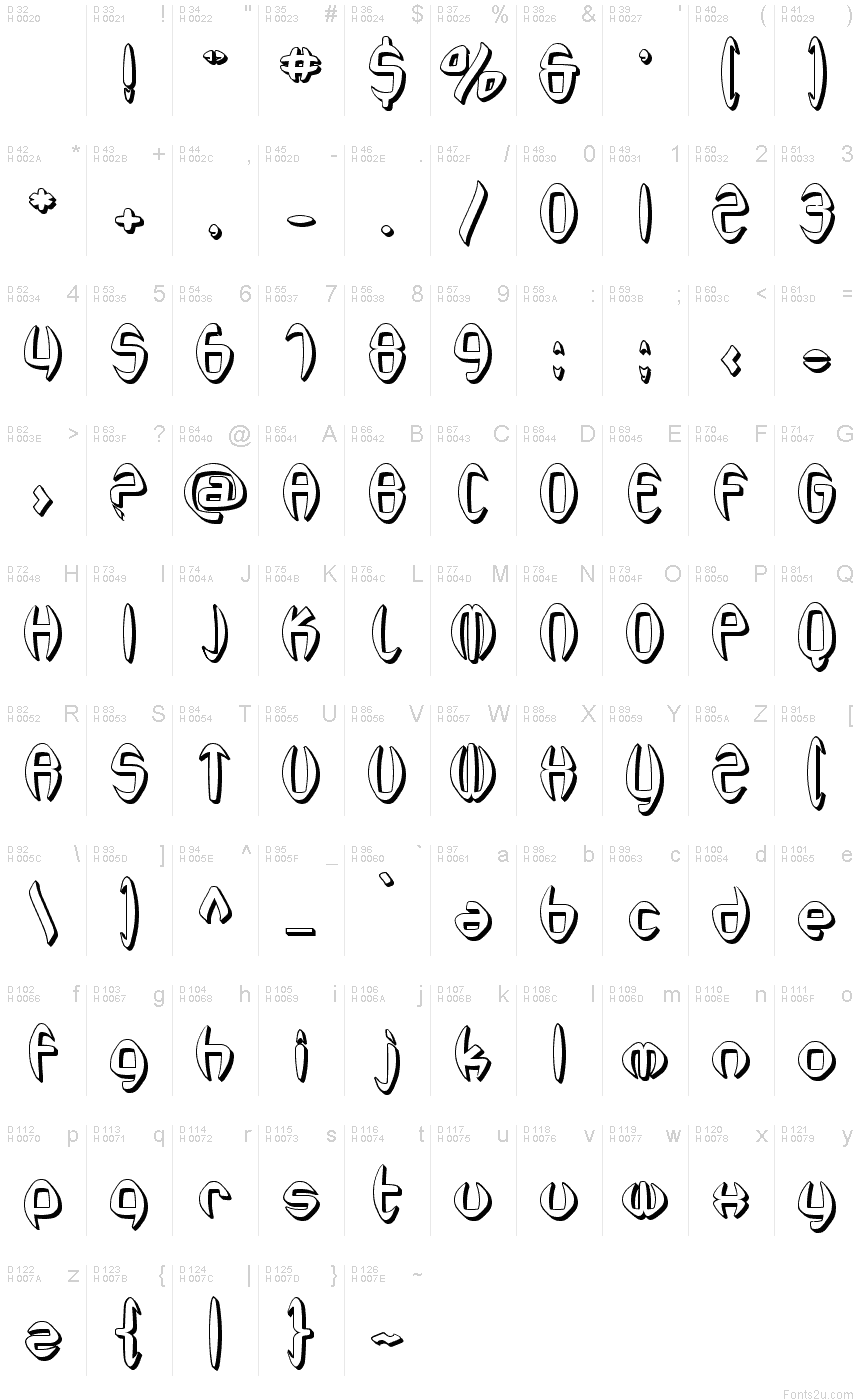
SF Synthonic Pop Shaded von ShyFoundry ist eine kostenlose, retro-futuristische Display-Schrift mit einem schwungvollen Space-Age-Look. Die Buchstaben bestechen durch weiche, voluminöse Kurven und tiefe Schatteneffekte, wodurch das Schriftbild nicht bloß skurril, sondern fast schon aufgeblasen und elastisch wirkt – eine Pop-Stimmung der späten 60er Jahre, die sich durch alle Zeichen zieht.
Sie passt perfekt zu Postern, Album-Art, Party-Flyern, Comic-Titeln und Cover-Lines, bei denen eine kostenlose Schrift eher Schwung als Perfektion braucht. Da die Großbuchstaben groß, geschwungen und leicht asymmetrisch sind, eignet sie sich zudem hervorragend für kurze Logos, Monogramme und Highlights, die diesen futuristischen Pop-Schimmer der alten Schule versprühen sollen, ohne steif zu wirken.